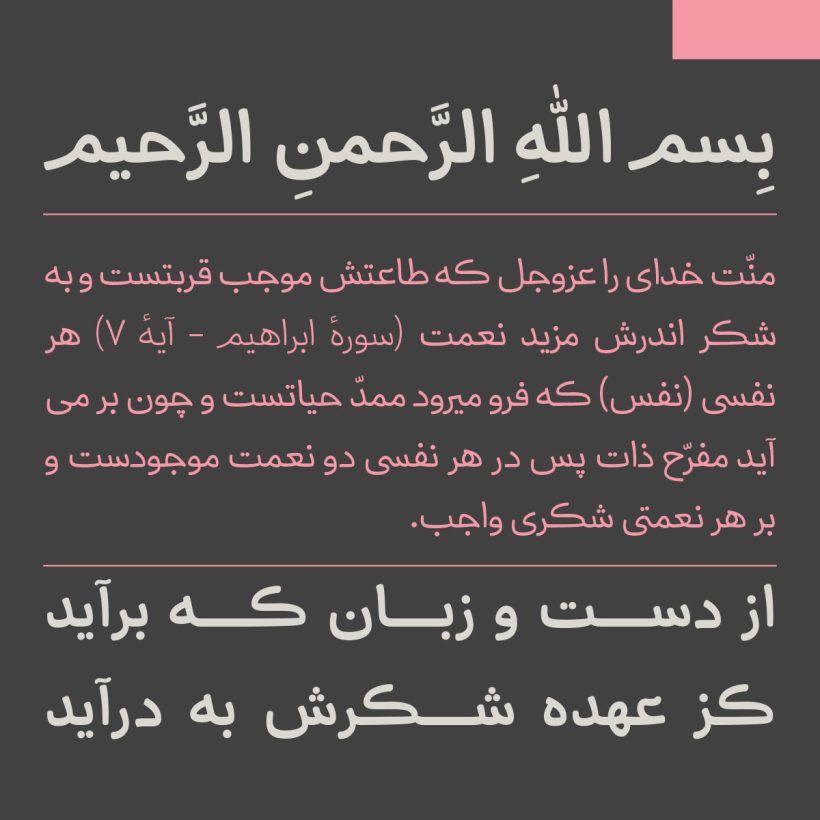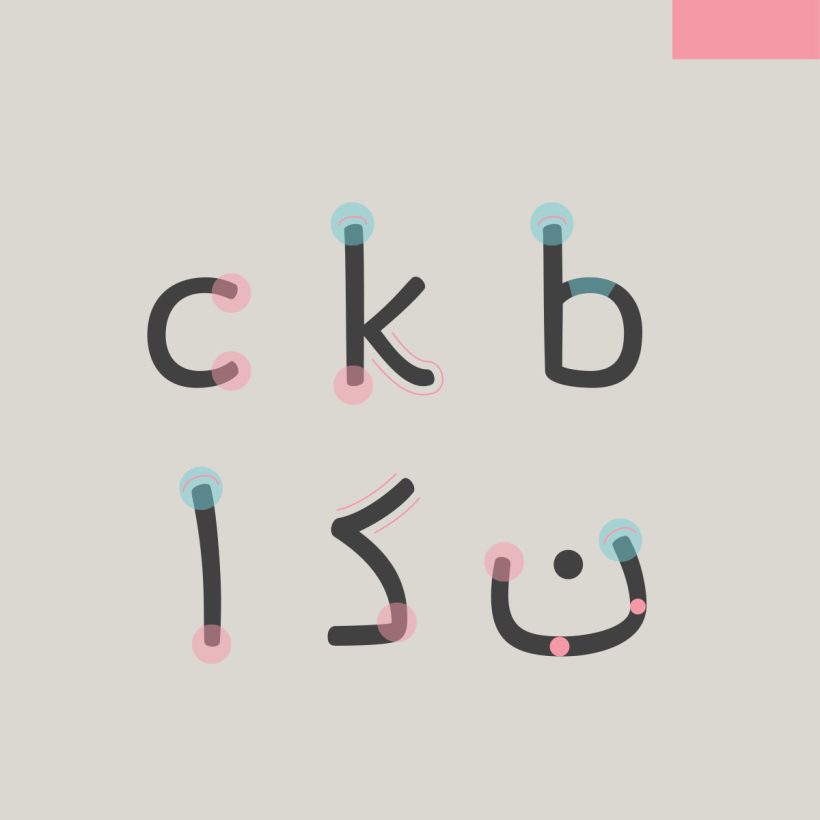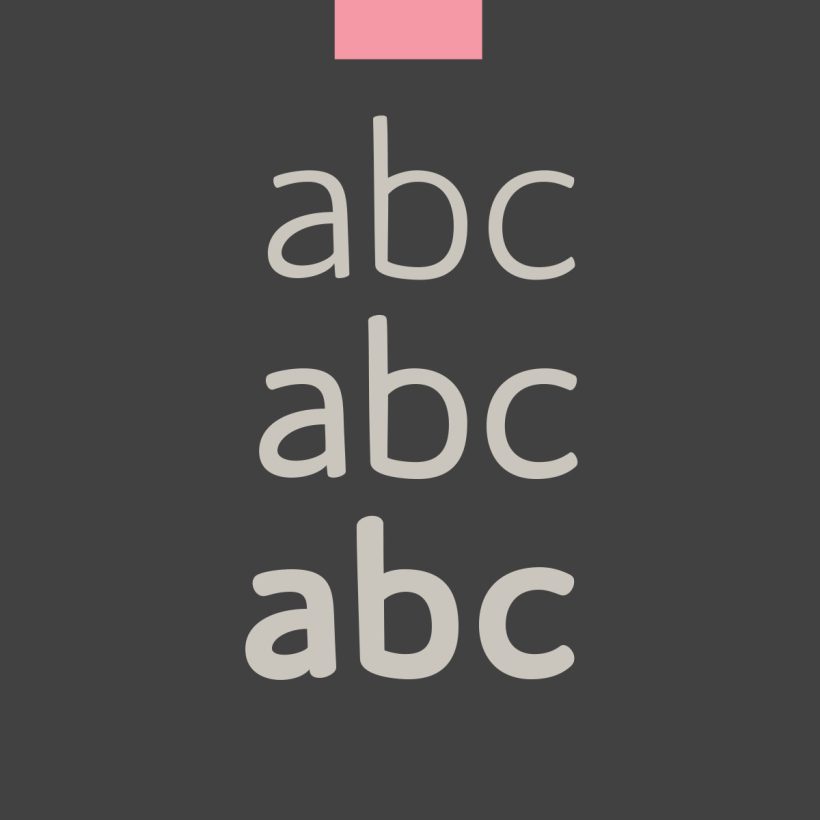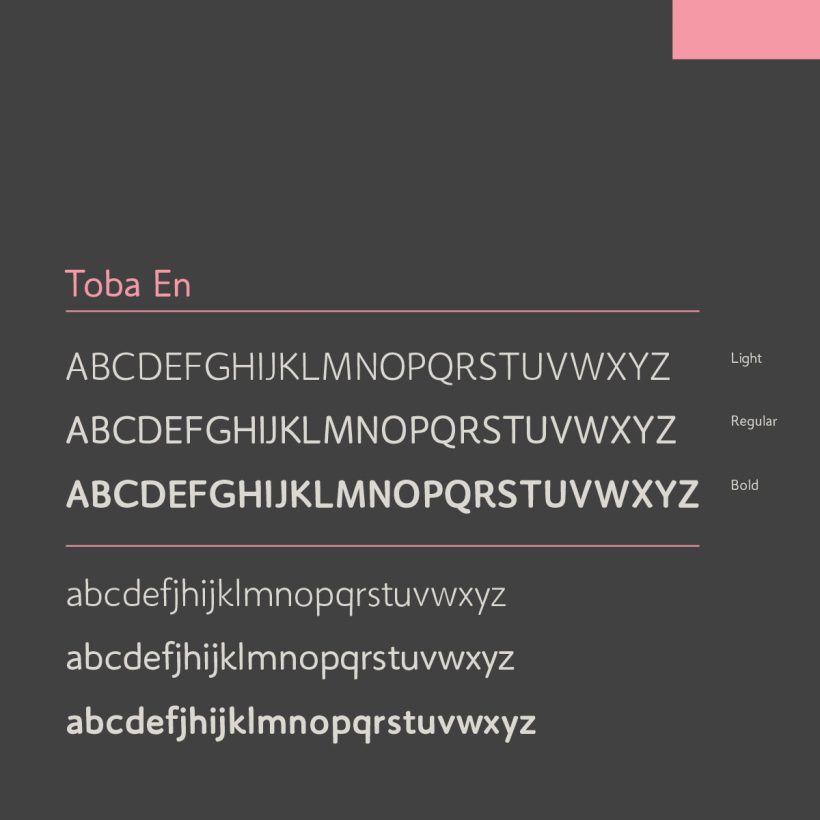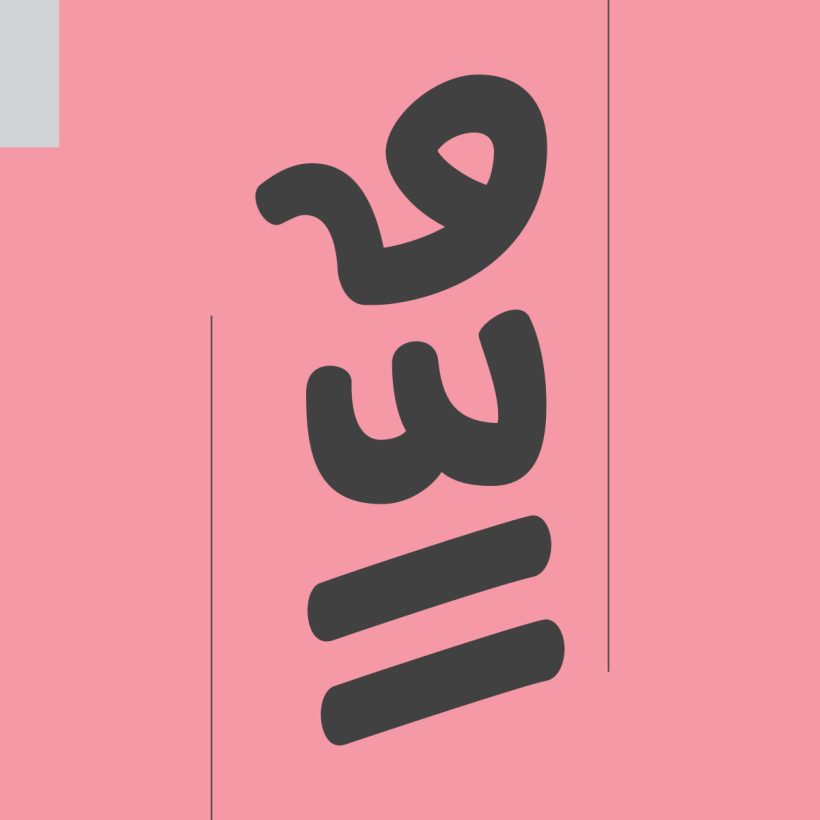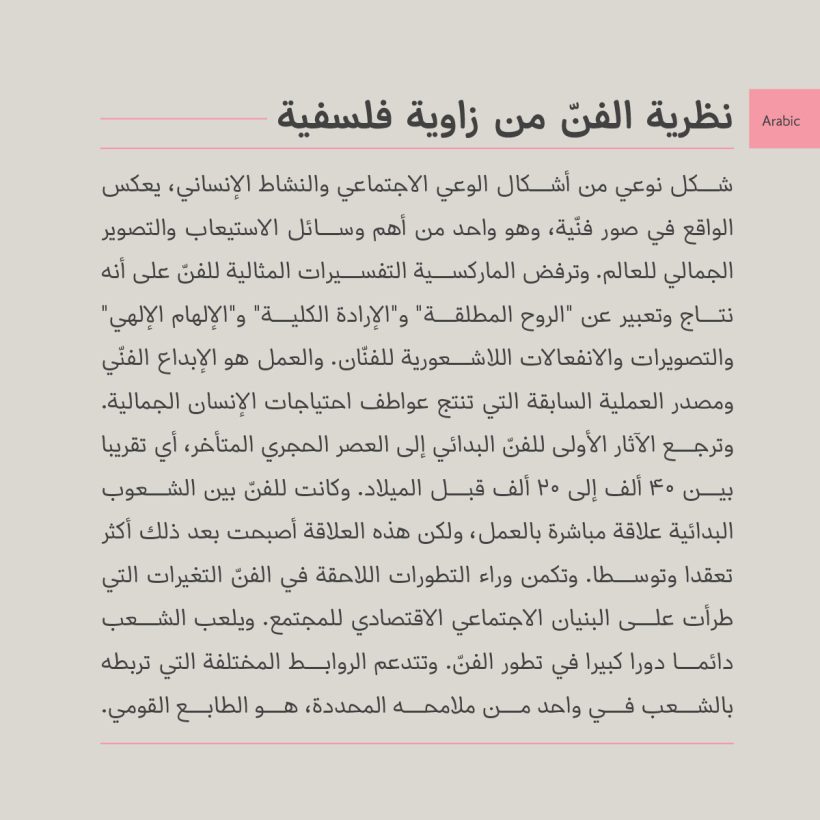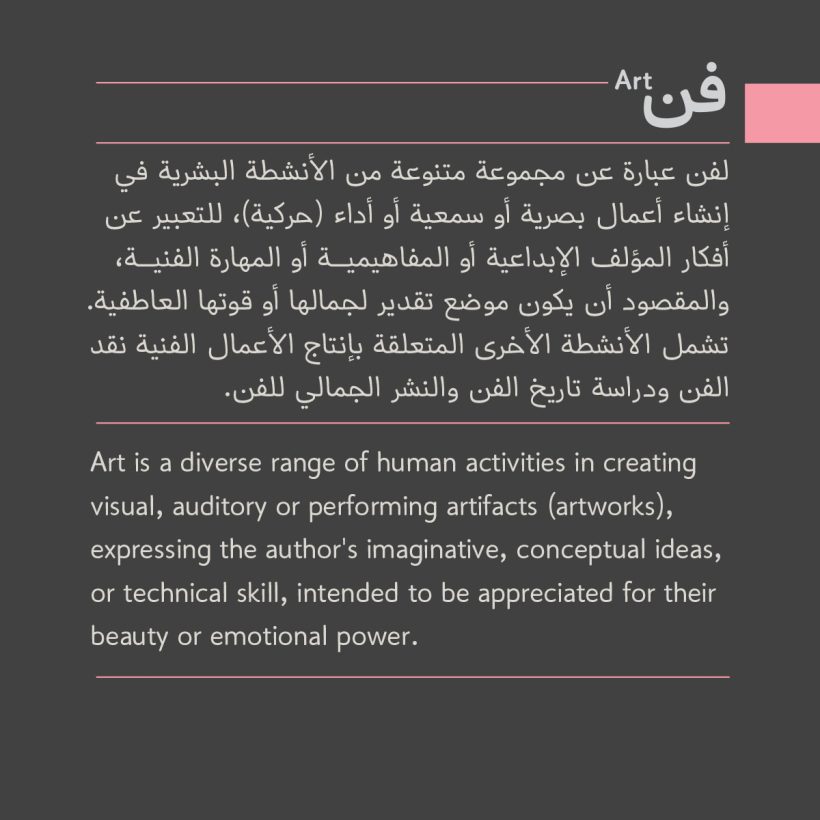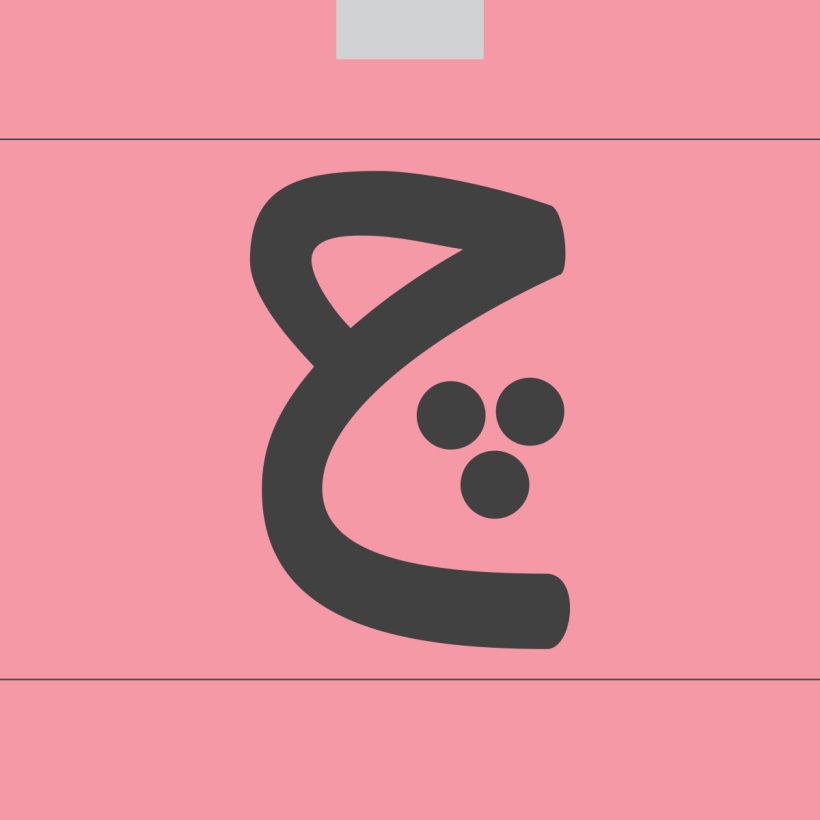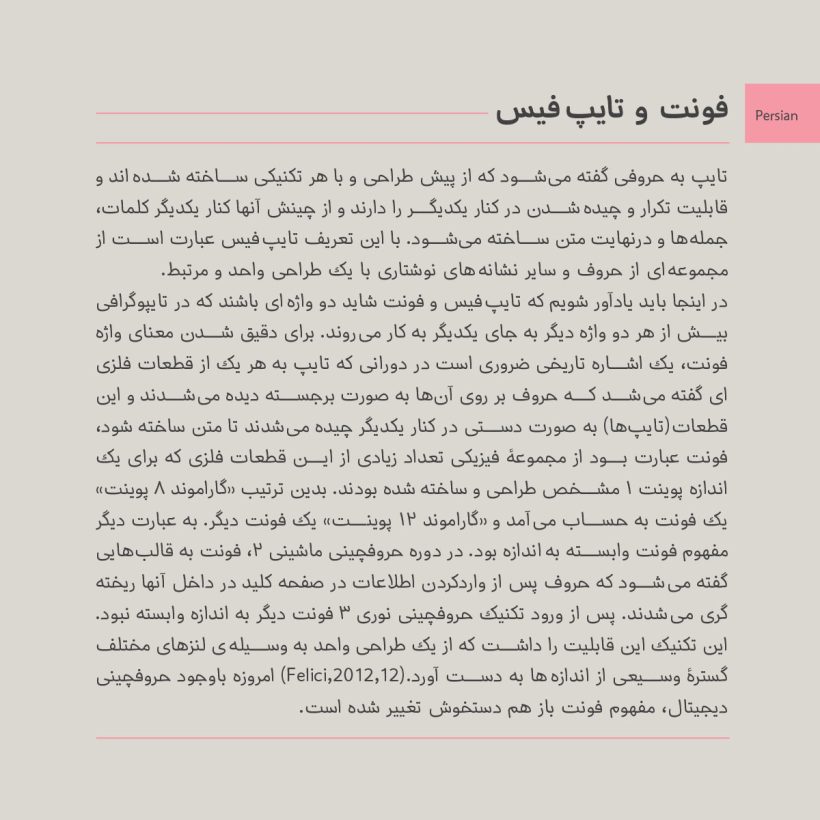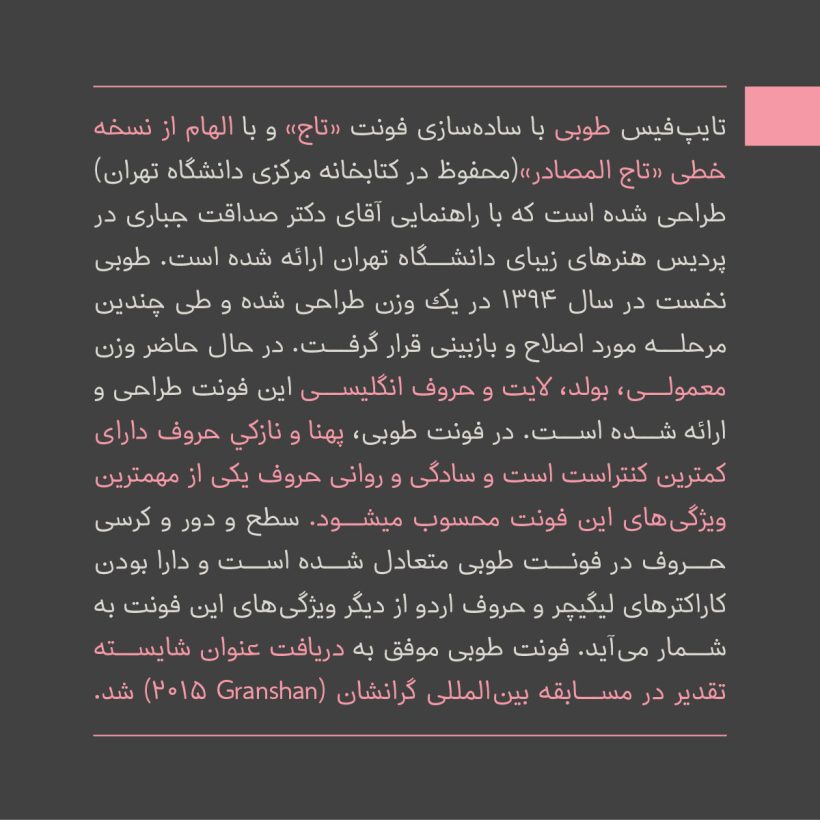
خانواده فونت طوبی
طوبی، فونت متن است و سه وزن لایت، معمولی و بولد را داراست. طوبی در یک نگاه، فونتی نو، سلیس، کارآمد و متفاوت است که در متن های کوتاه و بلند، خاکستری متعادل و لحنی هماهنگ دارد. حروف انگليسی طوبی، متناسب با حروف فارسی طراحی شده تا در مواقع نیاز پاسخگوی متن های لاتین باشد خصوصیتی که می تواند برای تولید کنندگان محتوا و کسب و کارها حائز اهمیت باشد. طوبی، لحنی سهل و ممتنع دارد و سادگی و روانی حروف یکی از مهمترین ویژگیهای این فونت محسوب می شود. در فونت طوبی پهنا و نازکی حروف دارای کمترین کنتراست است؛ سطح و دور و کرسی حروف متعادل شده است و پشتیبانی از زبان های اردو و کُردی از دیگر خصوصیات این فونت به شمار میآید. طوبی امکاناتی مثل لیگیچرها و امکان جایگزینی موقتی بعضی از حروف را بر حسب نیاز دارد و قواعد کرنینگ در آن اعمال شده است.
فونت طوبی با الهام از نسخۀ خطی «تاج المصادر»(محفوظ در کتابخانه مرکزی دانشگاه تهران) و با راهنمایی آقای دکتر صداقت جباری در پرديس هنرهای زيبای دانشگاه تهران طراحی شده است. طوبی موفق به دریافت عنوان شایسته تقدیر در مسابقه بینالمللی گرانشان (Granshan/2015) شد.